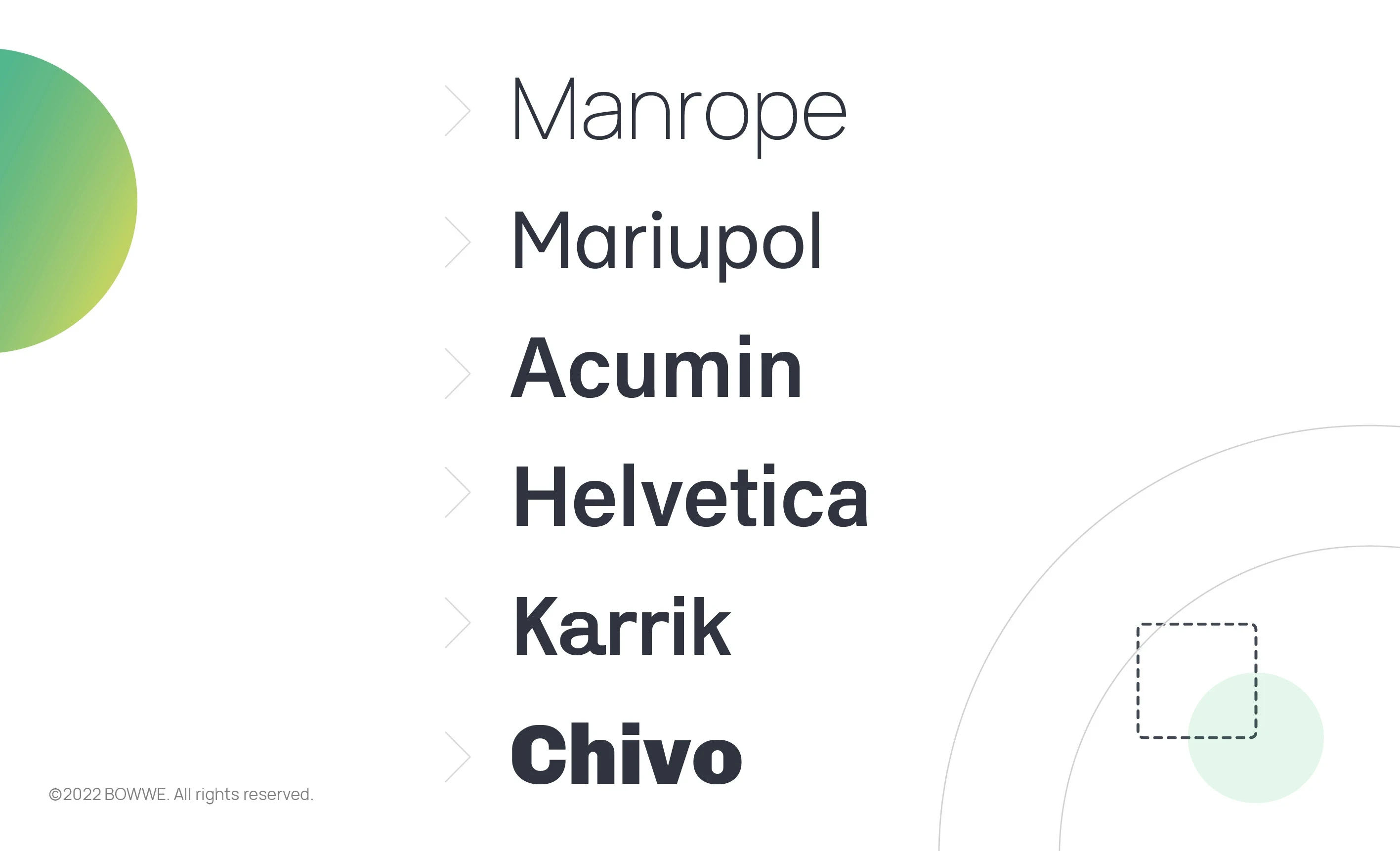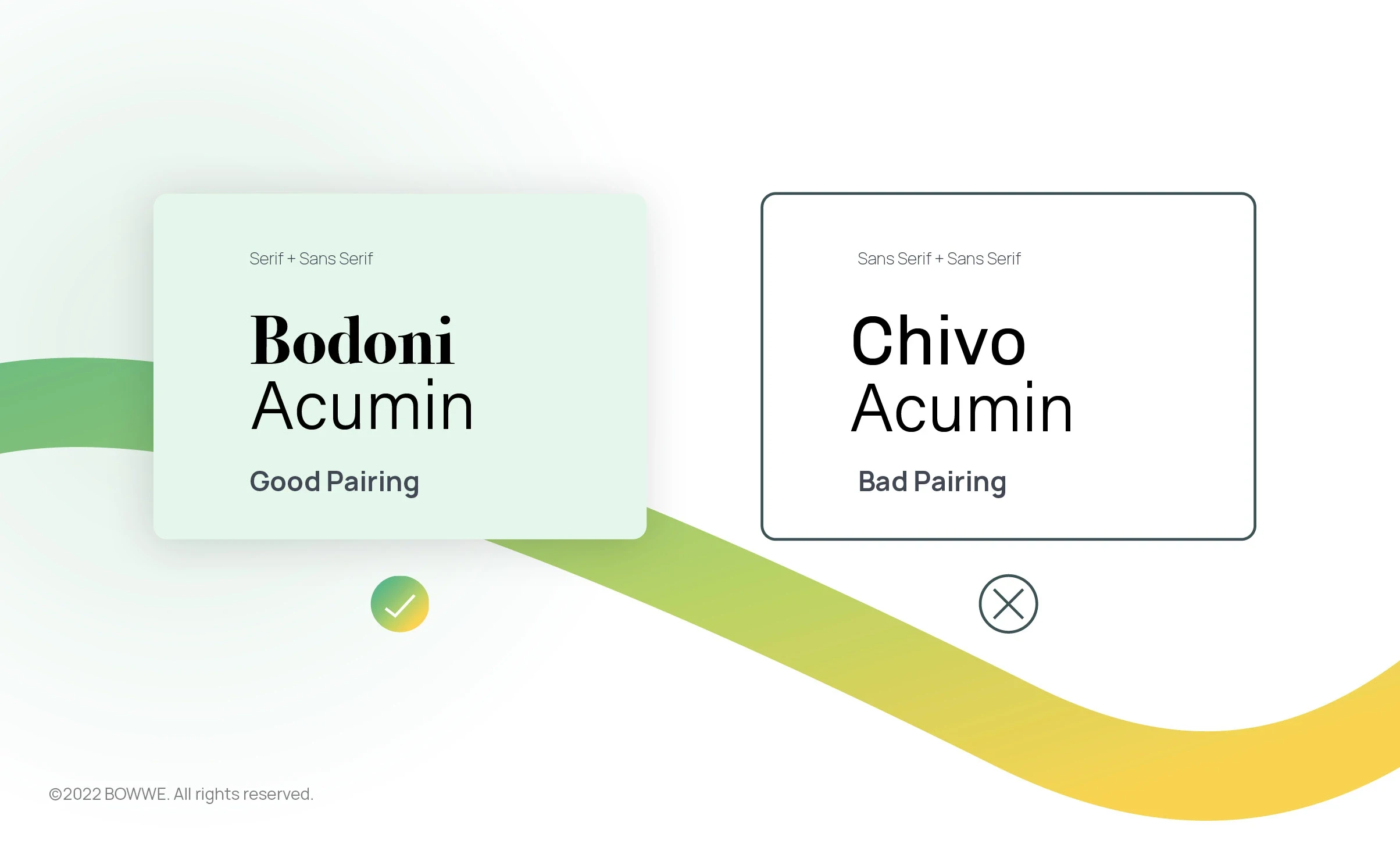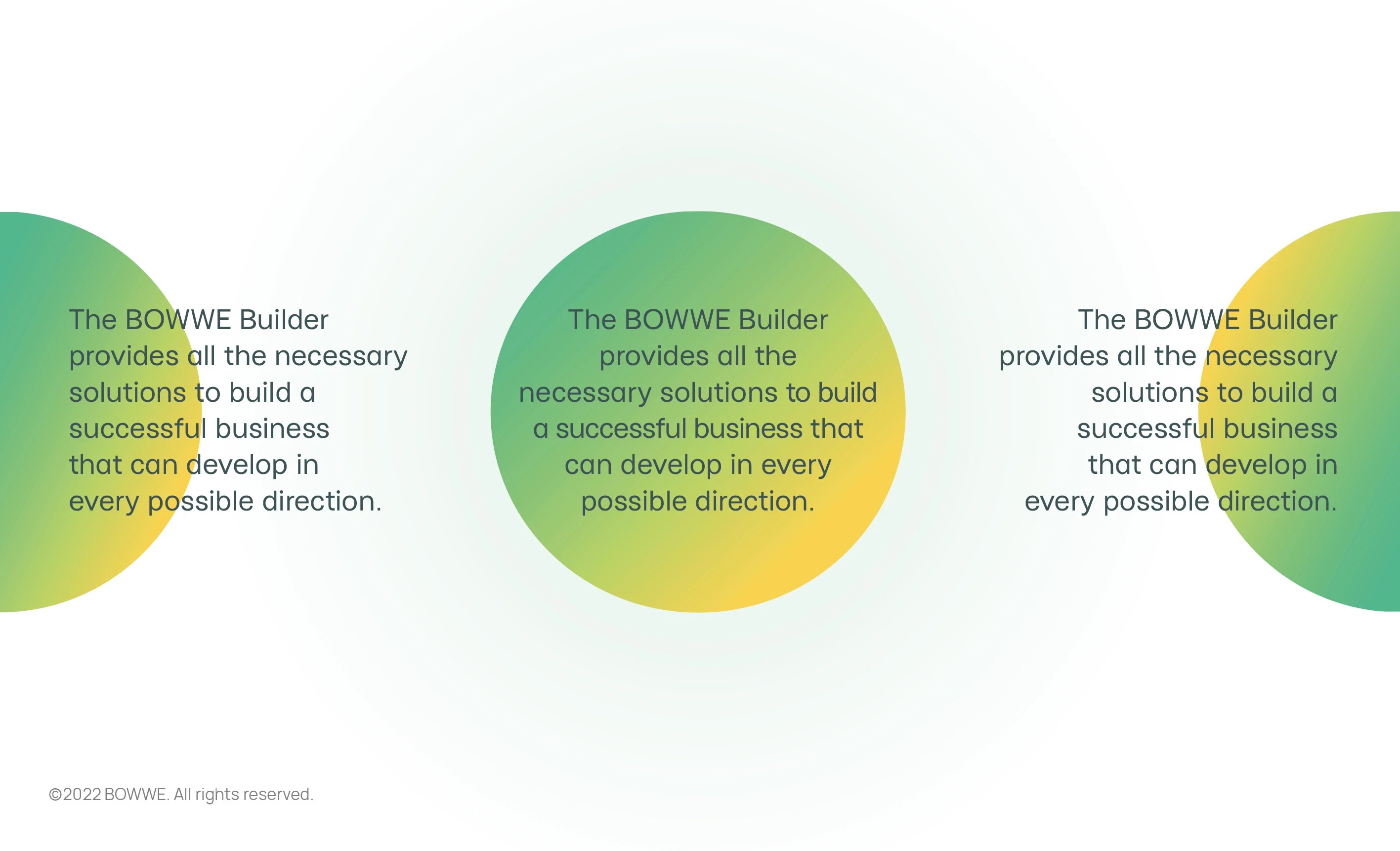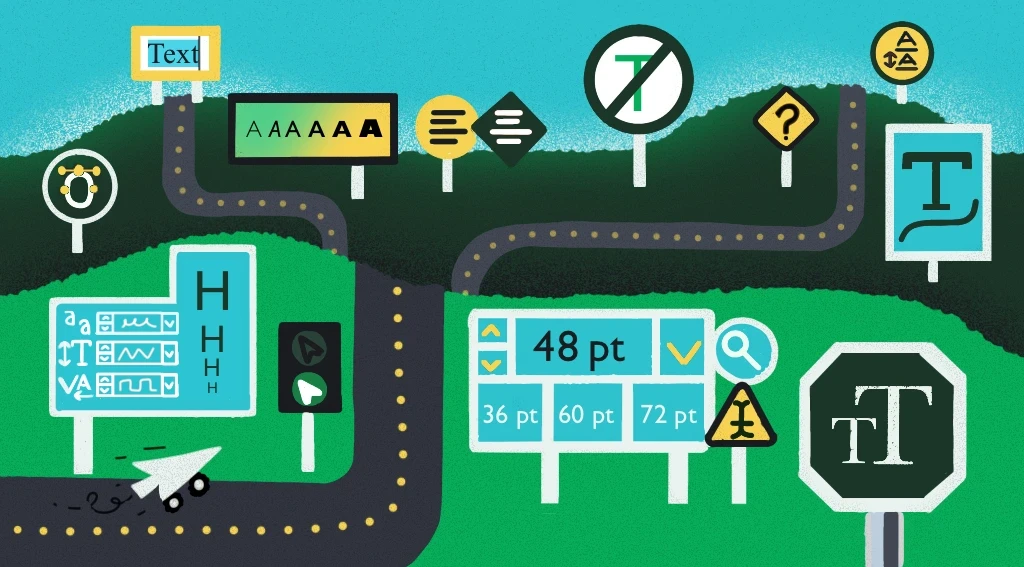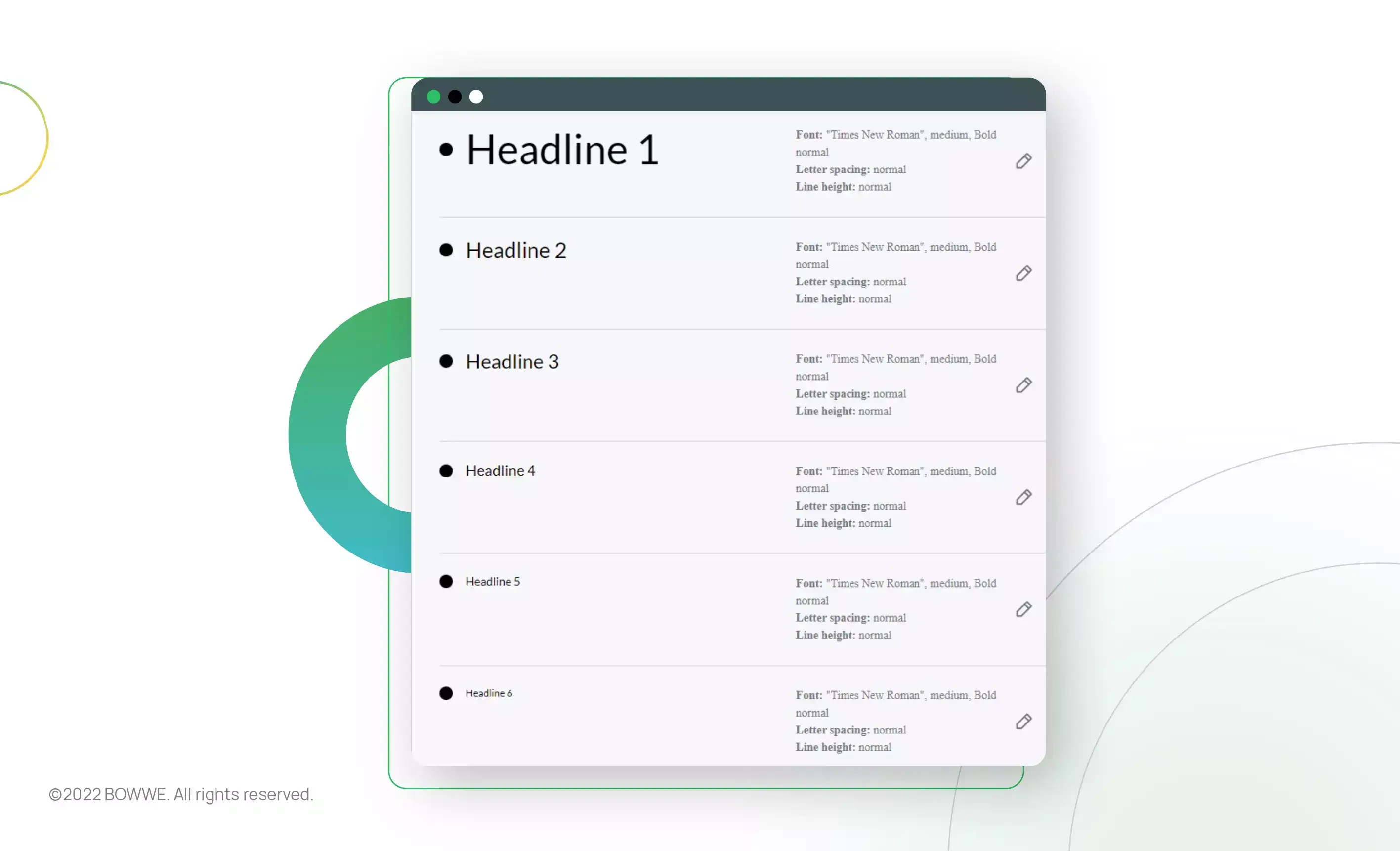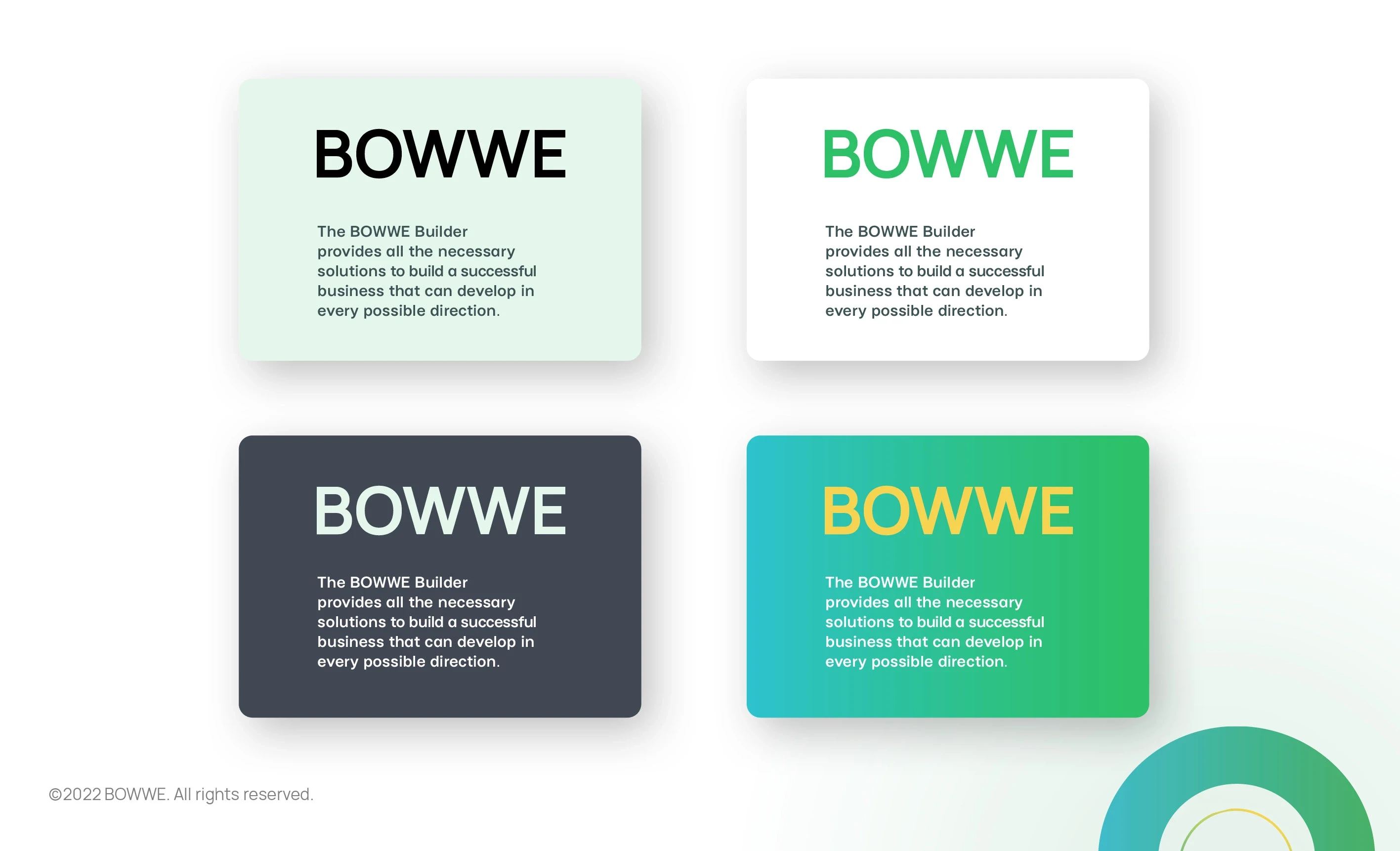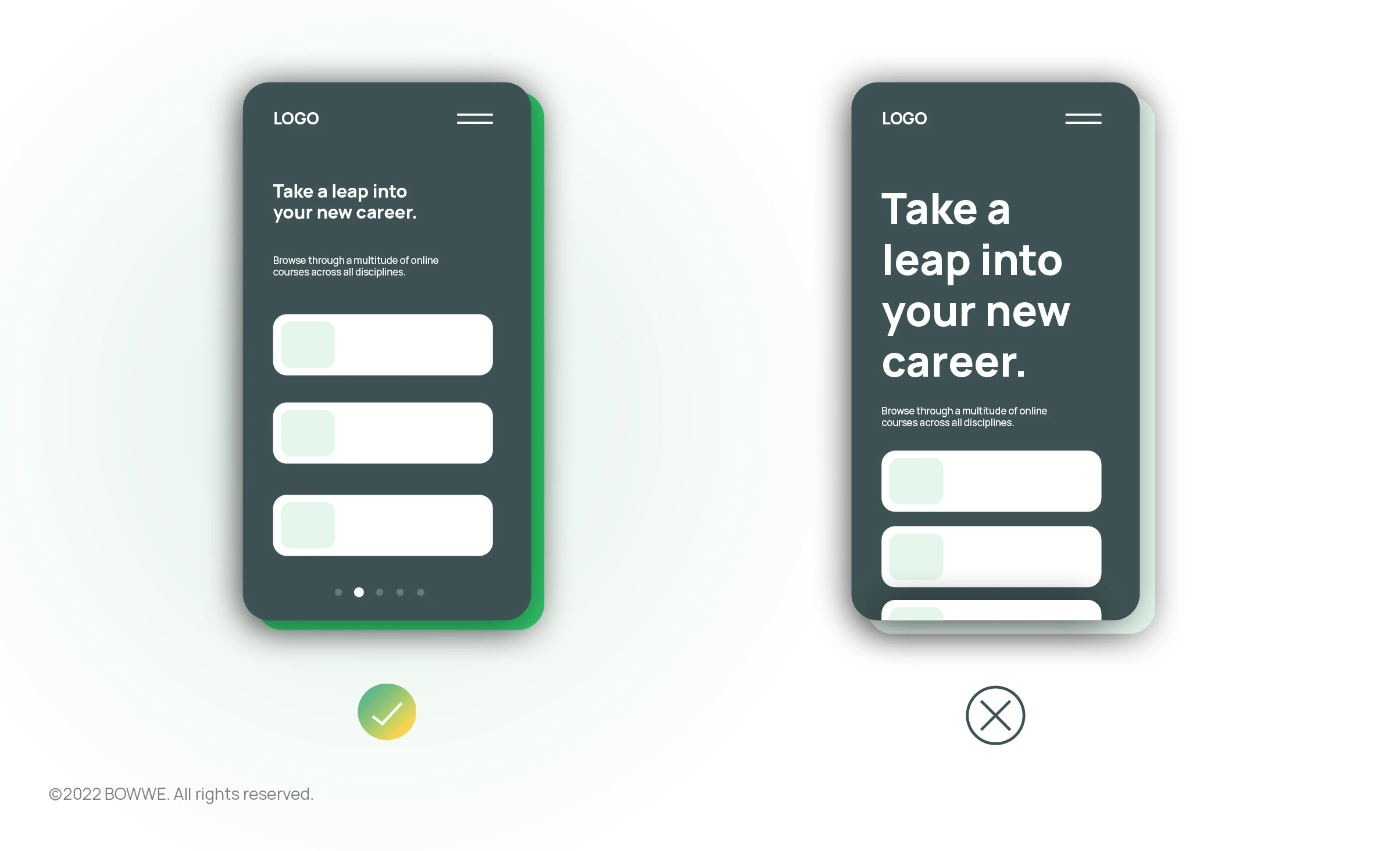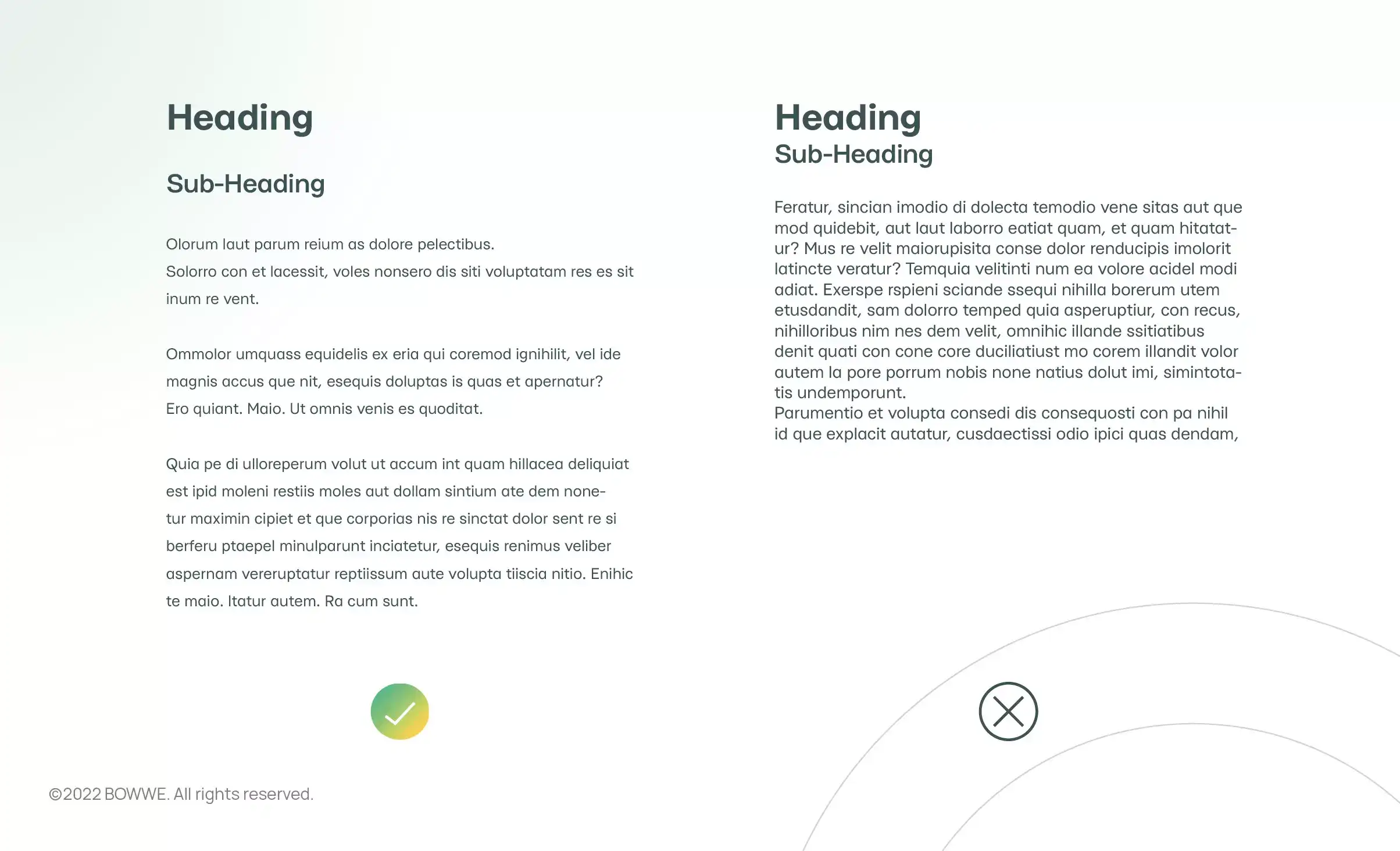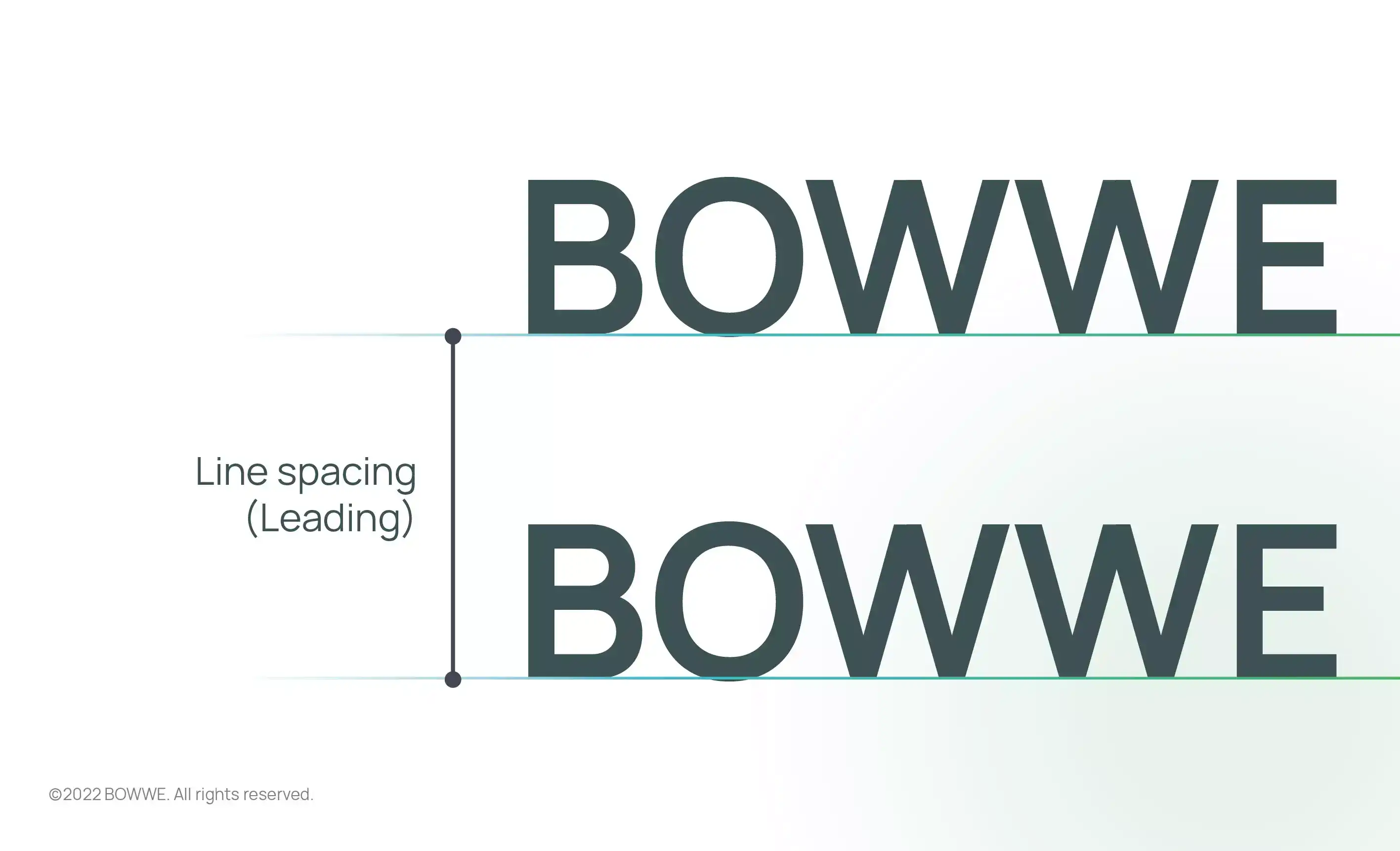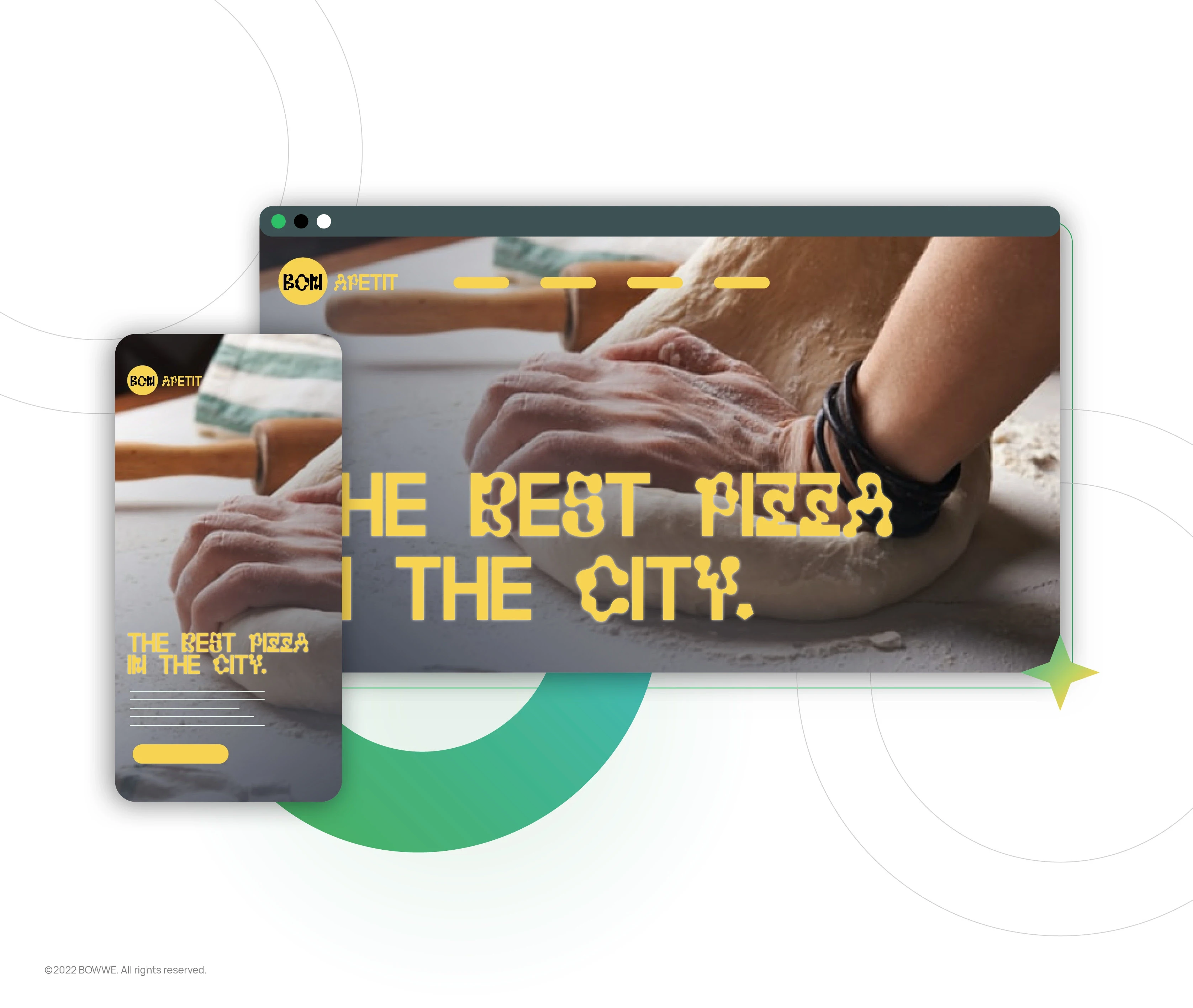
8 regras de tipografia de ouro para tirar o máximo proveito de suas fontes
Uma tipografia bem pensada e bem escolhida é a chave para alcançar um site esteticamente agradável e, o mais importante - facilmente legível. Mas você sabe como deixar o texto do site claro e consistente com a identidade da sua marca?
Não se preocupe. Reuni as 8 regras de tipografia mais importantes que tornarão todo o processo de criação da tipografia perfeita para o seu site fácil e eficaz. Certifique-se de seguir todas as regras e você será recompensado com um sistema de tipografia transparente que fará com que seu projeto pareça profissional e melhore seu UX.
8 princípios de tipografia a seguir
1. Escolha a fonte certa
O mais importante é que sua tipografia reflita a verdadeira natureza do seu setor. Portanto, escolher a tipografia certa para o site não pode ser uma questão de sorte. Só porque uma fonte é popular e você gosta dela, não significa que ela será apropriada para sua marca. Preste atenção ao que a fonte comunica e se ela combina com o estilo da sua marca.
Gráfico - Escolha a fonte certa
Preste atenção ao que a fonte comunica e se ela combina com o estilo da sua marca. Se você administra uma loja infantil, não usará fontes comerciais simples e elegantes e vice-versa. Sempre combine as fontes com a comunicação da sua marca para ser consistente com ela.
2. Selecione o tamanho da fonte
O tamanho da fonte na página é importante! Se você escolher uma fonte que não seja muito pequena ou muito grande, facilitará muito a leitura para seus usuários. Uma unidade especial que os tipógrafos usam para descrever as fontes é "pt" ou "ponto".
O intervalo preferido de tamanhos de fonte padrão para sites é entre 14 e 25 pt. Fontes maiores podem ser reservadas para títulos - 20pt e acima , e para texto simples, o melhor intervalo é 14-18pt.
Gráfico - Selecione o tamanho da fonte
Independentemente do tamanho da fonte escolhido, certifique-se de que o tamanho da fonte:
a) torna o texto legível - tamanho de fonte de 12pt e inferior pode prejudicar significativamente a legibilidade;
b) corresponde ao tipo de letra - por exemplo, para sua fonte do sistema Roboto Google recomenda um mínimo de 16 pt. Por outro lado, San Francisco - a fonte utilizada, entre outras, em dispositivos Apple, deve ter no mínimo 18pt;
c) reflete o propósito do site - se a página não for dominada pelo texto, mas pelo design, você pode usar uma fonte menor. Também no caso de páginas interativas que incentivam o usuário a clicar em cada etapa, essa solução pode ser oferecida. Se, por outro lado, você está lidando com um site onde o texto domina, e a principal tarefa do usuário é ler (por exemplo, área do blog, portal de informações) - é melhor escolher uma fonte um pouco maior.
Como escolher o tamanho do cabeçalho?
Você já decidiu o tamanho da fonte do seu corpo de texto, mas não sabe como manter o tamanho dos títulos em proporção ao restante do conteúdo? Existem várias práticas recomendadas para isso:
a) O cabeçalho H1 deve ter 300% do tamanho da fonte usada no corpo do texto. Por exemplo, se seu site usa uma fonte de 18 pt para o corpo do texto, o tamanho ideal para seus títulos é 54 pt.
b) O cabeçalho H2 deve ter 200% do tamanho da fonte do corpo do texto. Neste caso, com um tamanho de fonte base de 18pt, o cabeçalho H2 ideal seria 36pt.
⚡ BOWWE Tip:
Para títulos sucessivos, você pode diminuir gradualmente a porcentagem; por exemplo, para o cabeçalho H4, você pode multiplicar o tamanho da fonte primária por 130-150%.
Fontes na versão móvel
Gráfico - Fontes na versão móvel
Ao escolher o tamanho da fonte, você deve responder à pergunta em quais dispositivos o texto será exibido. O tamanho da fonte será diferente em monitores de laptop e em dispositivos móveis. Se você preferir focar na aparência do site em dispositivos móveis, lembre-se dessas duas regras importantes:
a) Em telas de smartphones, uma fonte grande não ficará legal,
b) Os títulos não devem ter mais de duas linhas.
Portanto, ao projetar um site para dispositivos móveis, vale a pena verificar a aparência do texto e verificar se a fonte é muito grande.
3. Use o princípio: menos é mais